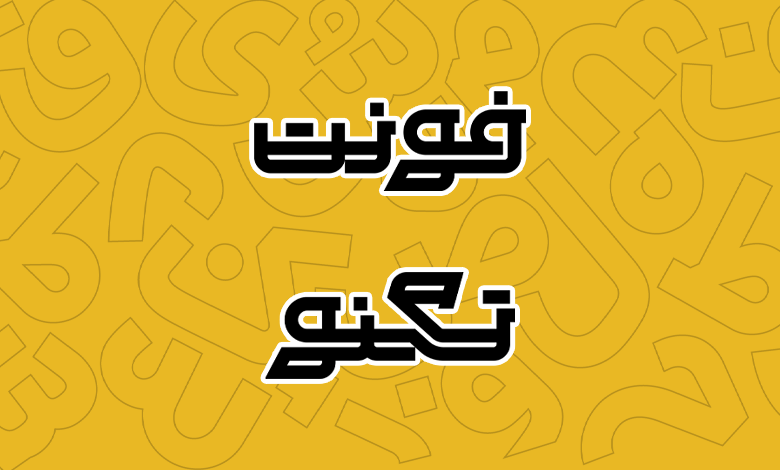
فونت تکنو (Techno)
فونت تکنو (به انگلیسی: Techno) ساختار هندسی با وزن Regular اما ظاهری فانتزی و درشت دارد. این فونت برای تبلیغات، طراحی پوستر، جلد مجلات، کتاب و بهطور کلی عناوین مناسب است. پشتیبانی از زبانهای فارسی، عربی، انگلیسی و کردی، وجود حروف و ترکیبات جایگزین همراه با اعداد فارسی از ویژگیهای دیگر این فونت است.
طراحی این فونت توسط نرگس همایون دانشآموخته کارشناسی فناوری اطلاعات انجام گرفته که در زمینه تایپ و لوگو فعالیت درخشانی دارد. توسعه قلم نیز توسط امین عابدی انجام شده که فونتهای متعددی از وی تاکنون در فونتچی معرفی شده است.
} ساختار این فونت بر اساس بازی هوشمندانه و هندسی با خطوط موازی طراحی شده است. جایی که خطوط موازی و مورب در هم تنیده شده و یک فونت با کنتراست بالا و ظاهری مدرن را خلق کرده است. در این فونت خطوط در راستای هم نیستند، بلکه با نقش مکمل و جریان همرفتی که هرکدام ایجاد میکنند، ظاهری فانتزی به این قلم میدهند که برای تیترنویسی و کارهای گرافیکی هنری مناسب است.